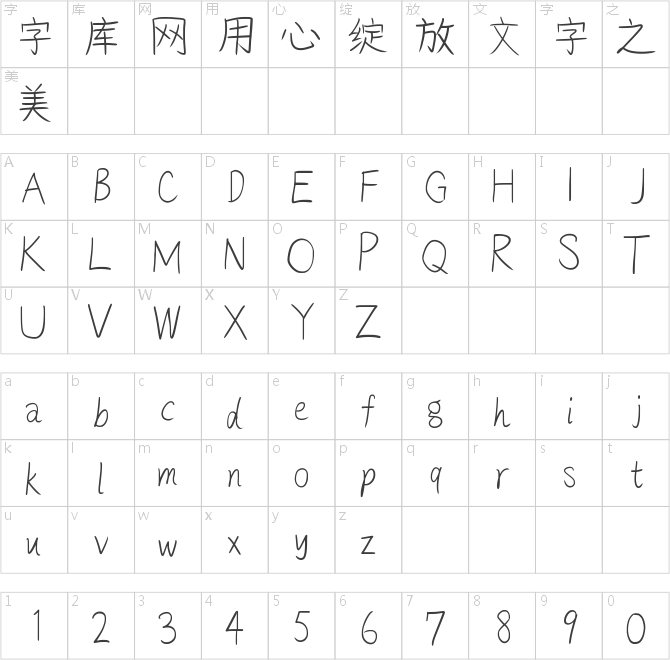
字体名称: Acy手写体
Acy手写体
Acy手写体介绍
这一款手写体是我们国内设计师 lxfly2000 做的一款字体,他是在B站做FontForge视频教学时放出的这一款字体
Acy手写体字体Acy字库是一款让人赏心悦目、百看不厌的中文字体,适合各类广告和产品包装设计应用,字体大小5.49MB,格式为ttf字体,上传用户是东方时尚,作者/版权方为lxfly2000